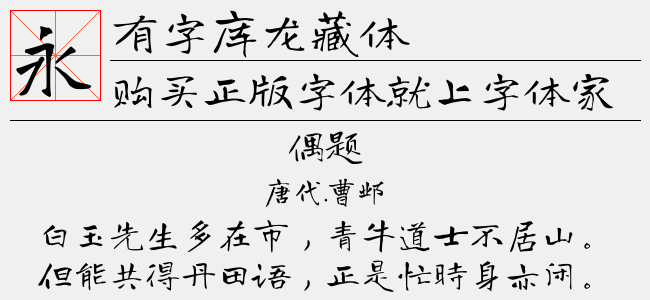
有字库龙藏体-佚名
有字库龙藏体是一款大小4.91 M的佚名字体,主要特征是手写,包装,手书风格,免费商用,钟齐免费商用,,有字库龙藏体为TTF格式的文件,采用安装嵌入,包含了符号拉丁文日文中文,字宽中等(正常),当前版本是Version 1.000,共计6763个汉字以及附加其他英文字体和阿拉伯数字。
字体名称:有字库龙藏体